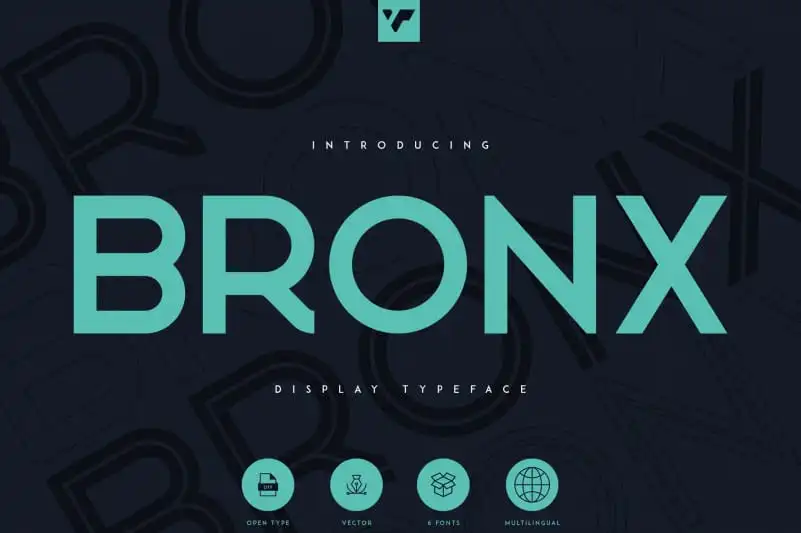
Bronx – Sans Serif Font – Download Grátis
Bronx é uma fonte séria sem serif que oferece uma experiência visual casual e clara. Com seis estilos distintos, esta fonte pode ser usada tanto em grandes como em pequenos tamanhos, tornando-a extremamente versátil. Seja para textos do site ou logotipos empresariais, Bronx é perfeita para qualquer aplicação que exige uma aparência moderna e despojada. Com seu design limpo e casual, ela se destaca em qualquer layout gráfico, tornando-a a escolha ideal para quem deseja um estilo clean sem abrir mão de sua legibilidade excepcional. Inspirado no estilo urbano e na cultura da cidade, esta fonte é perfeita para designers que desejam incorporar elementos modernos e únicos em seus projetos visuais.